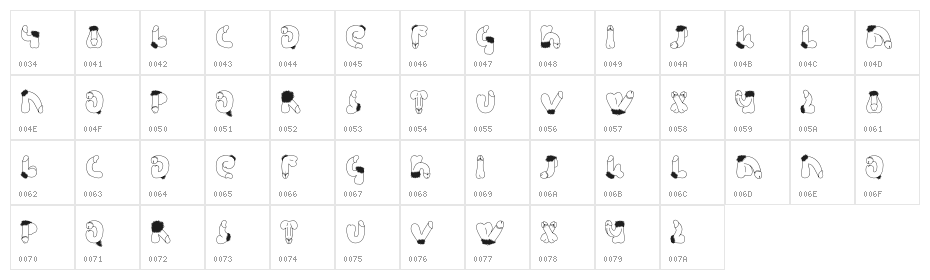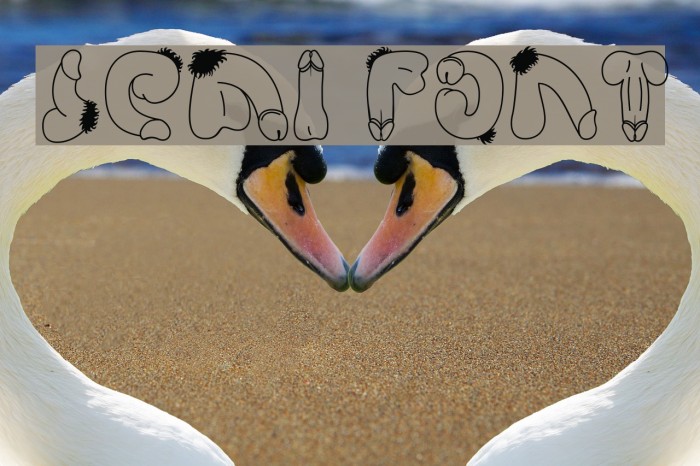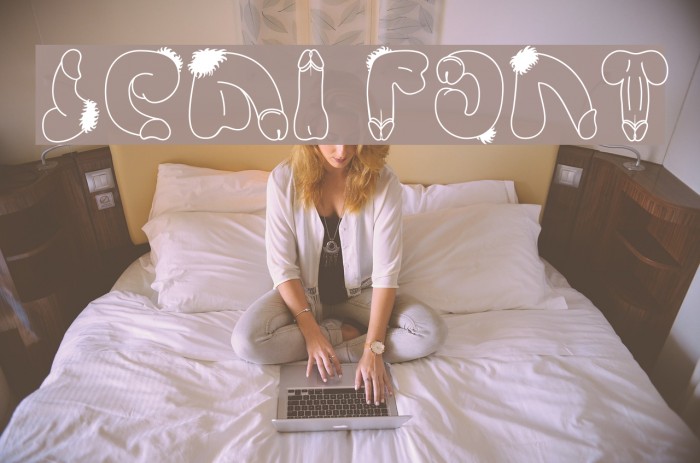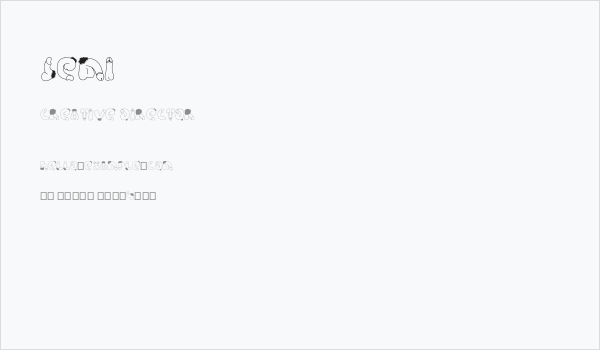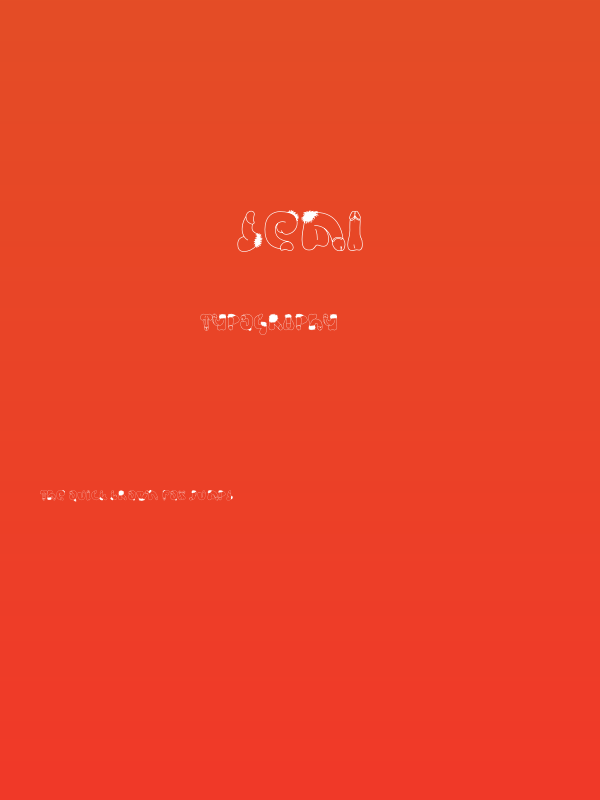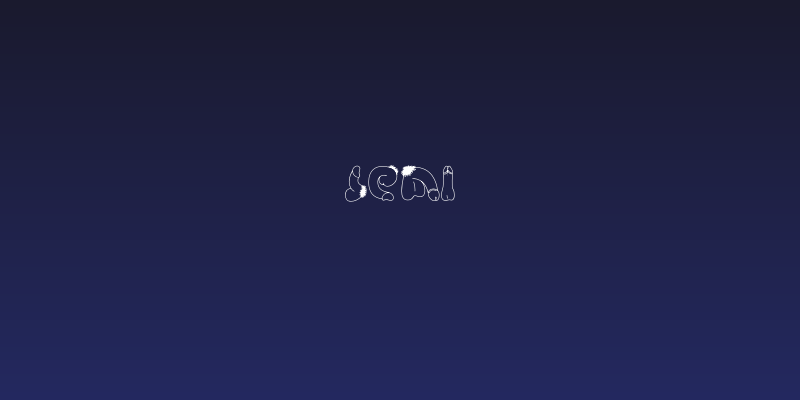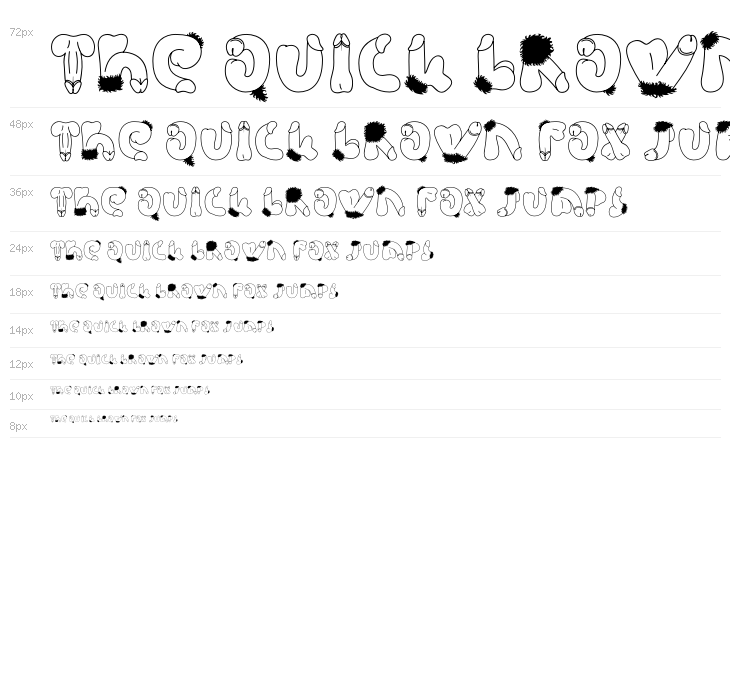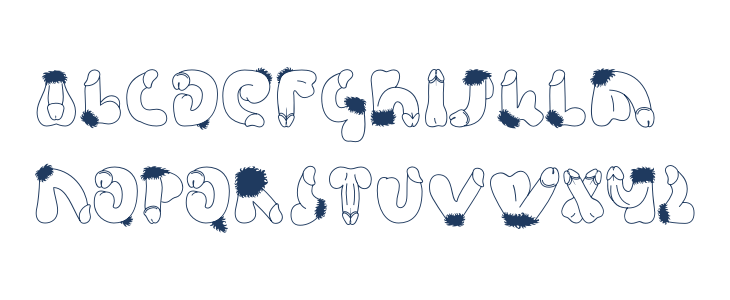
Semi Font
| Stile generale | Humorous, Playful, Quirky |
| Caso d'uso | Logos, Posters, Greeting Cards |
| Progetti proposti | Ideal for novelty posters, humorous greeting cards, playful branding, or any project seeking a bold and cheeky aesthetic. |